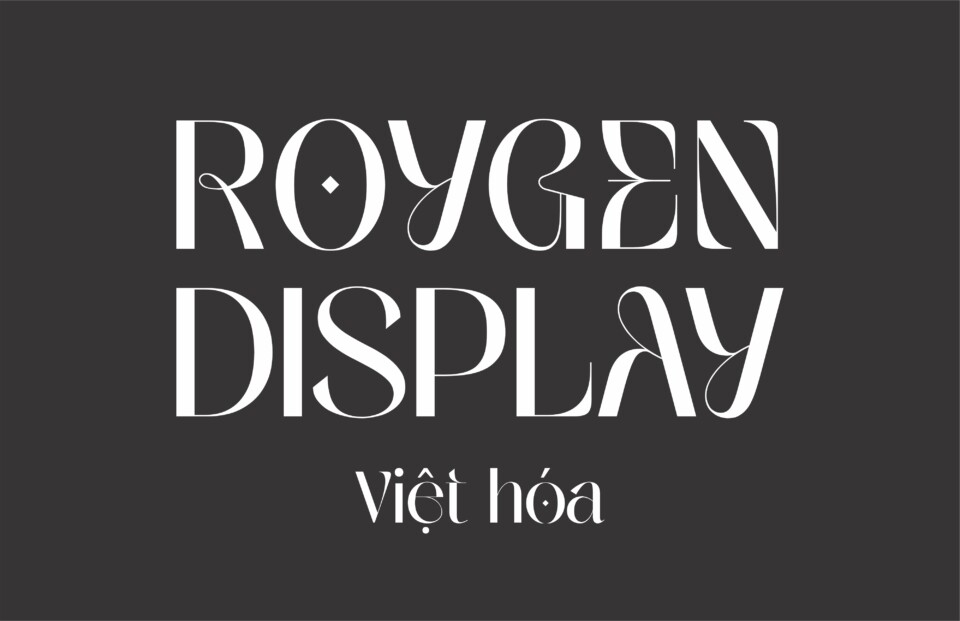
Font Việt hóa VN Roygen Display
Giới thiệu về Font Việt hóa VN Roygen Display
Trong thế giới đồ họa hiện đại, việc lựa chọn một Font Miễn Phí chất lượng luôn là ưu tiên hàng đầu của các bạn học sinh và giáo viên. Font Việt hóa VN Roygen Display là một bộ phông chữ sở hữu phong cách sang trọng, thanh lịch nhưng không kém phần mạnh mẽ. Với đường nét được trau chuốt tỉ mỉ, bộ font này giúp các bài thuyết trình hay báo cáo học tập trở nên chuyên nghiệp hơn bao giờ hết. Đặc biệt, phiên bản việt hóa chuẩn giúp người dùng tự tin sử dụng tiếng Việt mà không lo lỗi hiển thị dấu câu.
Tại sao nên chọn Font Việt hóa VN Roygen Display?
Bộ chữ này mang đến sự cân bằng hoàn hảo giữa tính thẩm mỹ và khả năng đọc hiểu. Font Việt hóa VN Roygen Display cực kỳ phù hợp cho các tiêu đề lớn, banner sự kiện nhà trường hoặc bìa sách sáng tạo. Các ký tự hiển thị rõ ràng trên cả màn hình máy tính lẫn bản in, hỗ trợ tối đa cho quá trình học tập và giảng dạy sáng tạo.
Ứng dụng thực tế của bộ font trong học đường
Các bạn học sinh có thể dùng bộ chữ này để thiết kế slide PowerPoint sinh động, tạo điểm nhấn cho các dự án nhóm. Thầy cô giáo cũng dễ dàng ứng dụng vào việc làm thiệp chúc mừng, bằng khen hoặc trang trí bảng tin lớp học. Sự đa dạng trong độ dày mảnh của chữ giúp người dùng linh hoạt thay đổi phong cách từ cổ điển đến hiện đại một cách nhanh chóng.